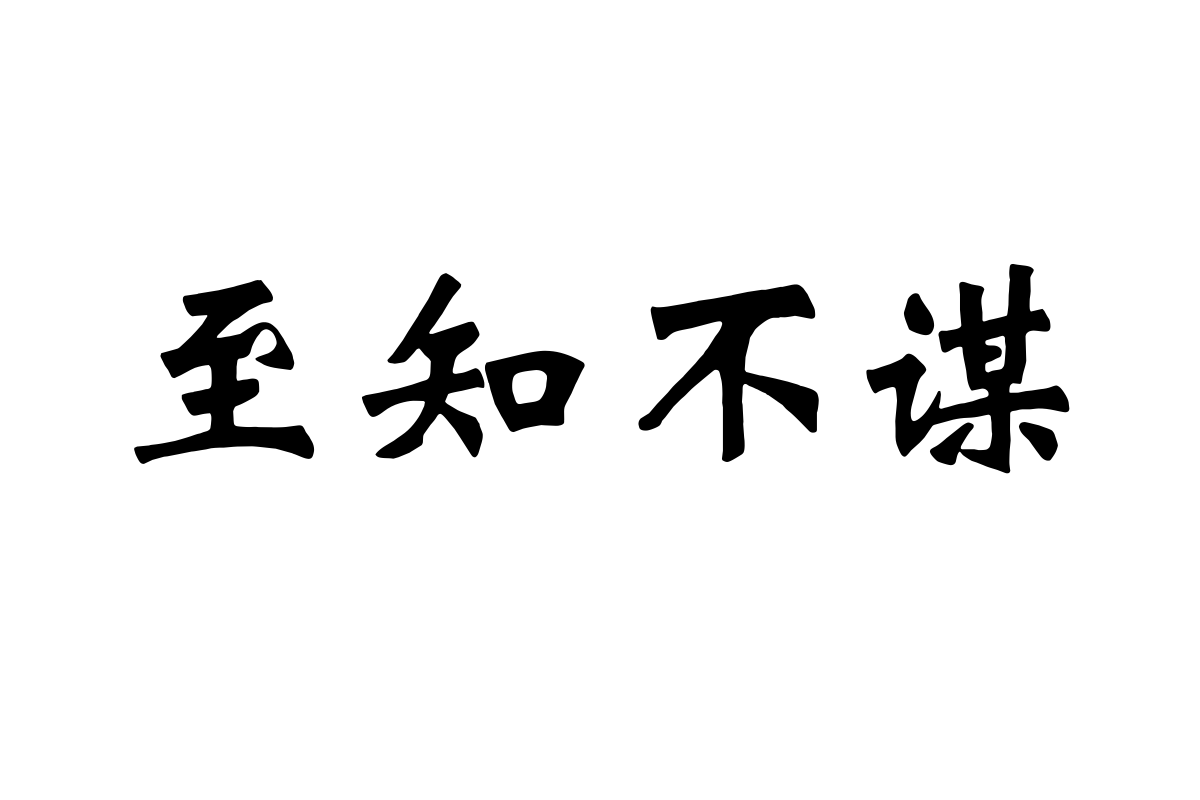
汉仪魏碑简字体是一款具有浓厚历史感和艺术风格的中文字体。它源自于汉代的魏碑,汲取了魏碑的精髓,融合现代设计理念,形成了一种独特的字体风格。
该字体的特点主要体现在以下几个方面:
1. 结构严谨:汉仪魏碑简字体采用了传统的楷书结构,笔画清晰,字形规整,给人一种庄重、古朴的感觉。
2. 笔画流畅:在保持传统楷书特点的基础上,汉仪魏碑简字体在笔画的处理上更加流畅自然,避免了过于生硬的线条,使得整体视觉效果更加和谐。
3. 字形饱满:汉仪魏碑简字体的字形饱满有力,具有很强的视觉冲击力,适合用于标题、广告等需要突出显示的部分。
4. 风格独特:汉仪魏碑简字体在继承传统书法艺术的基础上,又融入了一些现代元素,使其既具有古典韵味,又不失时尚感。
5. 适用范围广:无论是用于报纸、杂志、书籍还是网页设计,汉仪魏碑简字体都能展现出其独特的魅力,满足不同场合的需求。